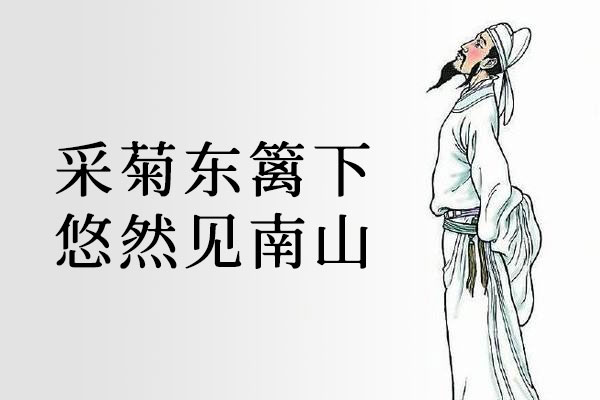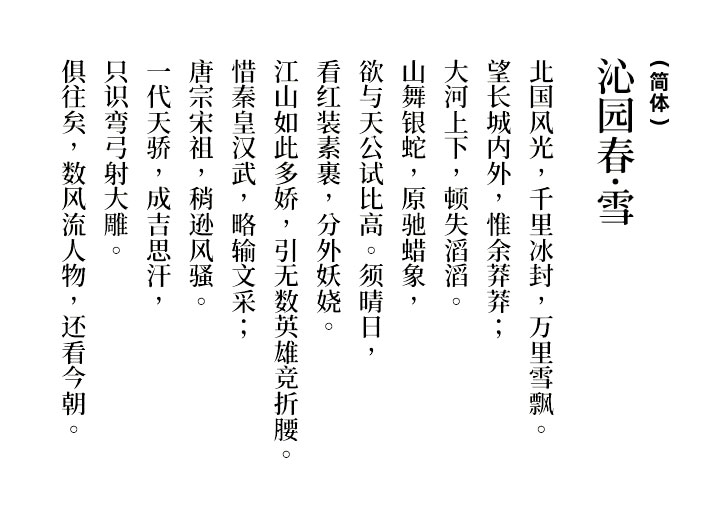
狮尾B2宋朝
狮尾B2宋朝字体(Swei B2 Serif CJKtc)是由中国台湾的MAX以思源宋体为基础精心打造的一款字体。通过独特的程序设计,他将字体中的转角三角形巧妙地转化为了半圆形,使得字体看起来仿佛带着淡淡的墨水晕染,或是轻微的曝光效果。这款字体支持简体中文、繁体中文、韩文和日文,欢迎广大用户自由应用、优化和二次创作。
狮尾B2宋朝字体拥有七个不同的字重,这意味着其具备丰富的字符种类,可以满足你在各种场合下的使用需求。由于是基于思源宋体改造,因此它的字符相当完整,你无需担心在应用过程中会出现缺字的情况。
狮尾B2宋朝效果预览